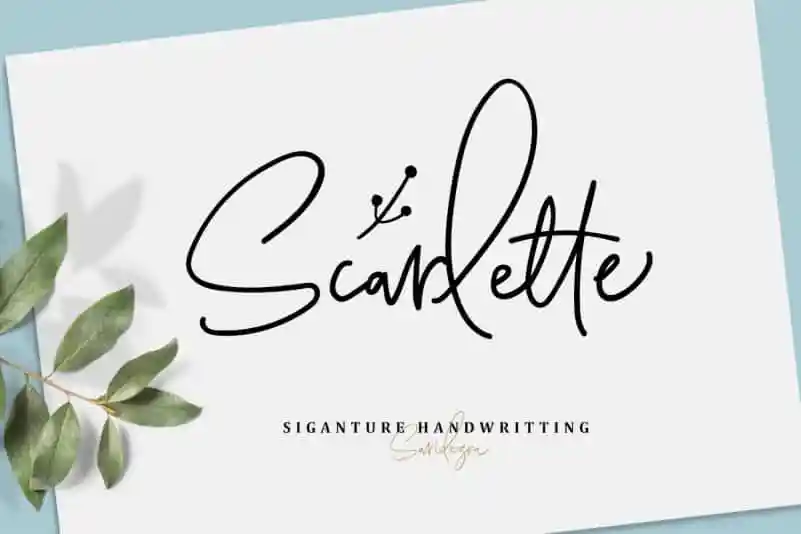
Scarlette Signature Font
A ‘Scarlette Signature Font’ é uma elegante escolha para aqueles que buscam uma fonte de script personalizada e sofisticada. Esta fonte é projetada para manuseio cuidadoso, com uma aparência íntima e natural do estilo da mão escrita. Ela incorpora ligaturas para criar um fluxo fluido e harmonioso que adiciona profundidade ao seu projeto. A ‘Scarlette Signature Font’ foi criada pelo designer Hamilton e é um elemento único capaz de personalizar sua marca, projetar criações fashionísticas, convidativas para festas de casamento ou até mesmo destacar citações escritas à mão. Obrigado a todas as oportunidades que você oferece para tornar seus trabalhos ainda mais especiais com ‘Scarlette Signature Font’, uma fonte única e versátil. Além disso, o designer incluiu um conjunto divertido de letras feitas à mão (doodle font) para permitir que você faça sua própria marca visual ou personalize qualquer design que desejar. Esta font é especialmente atraente para quem procura estilizar texto em linguagens multilíngues, e vem pronta com codificação PUA para maximizar a versatilidade do seu projeto.